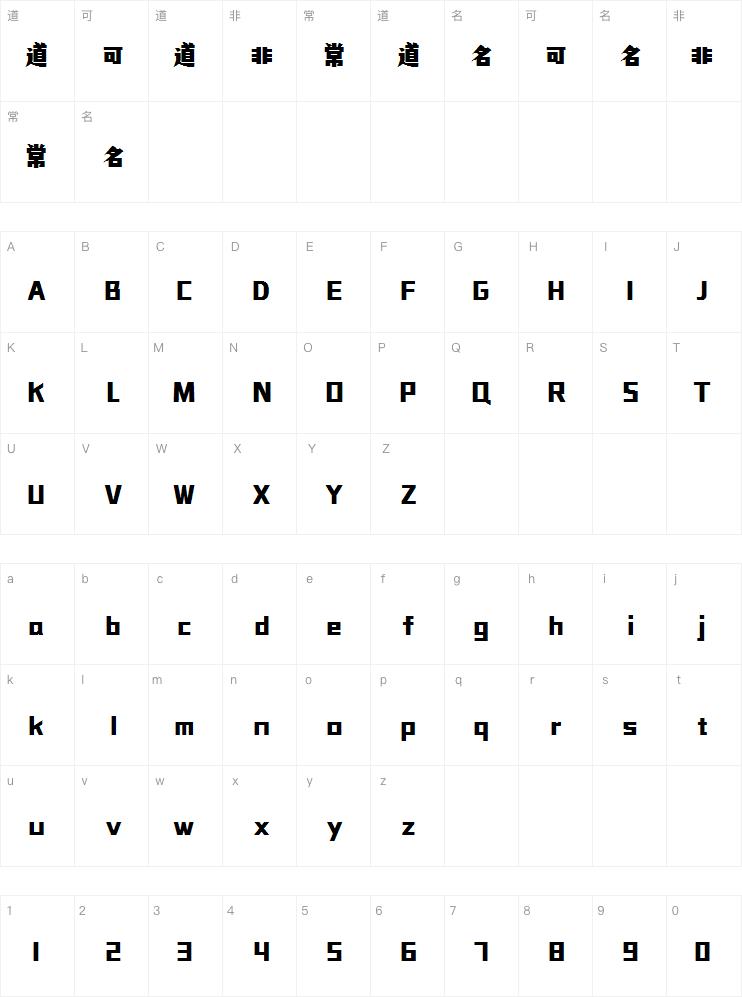
卓特自由体
卓特自由
卓特清雅体是卓特视觉(droitstock.com)携手国内知名字体设计师刘兵克为创意人群打造的开源字体。 这款字体字形结构灵动、大小错落,呈现出很强的节奏感。笔画粗实有力、几何感强极适合用于娱乐视觉、赛事主题、等需要强烈吸睛效果的场景。能塑造出张扬、俏皮带点力量感的整体气质。 本字体包含 GB2312-80 标准中的 6763 个简体汉字及 420 个常用字符,共收录 7183 个字符,可免费商用。